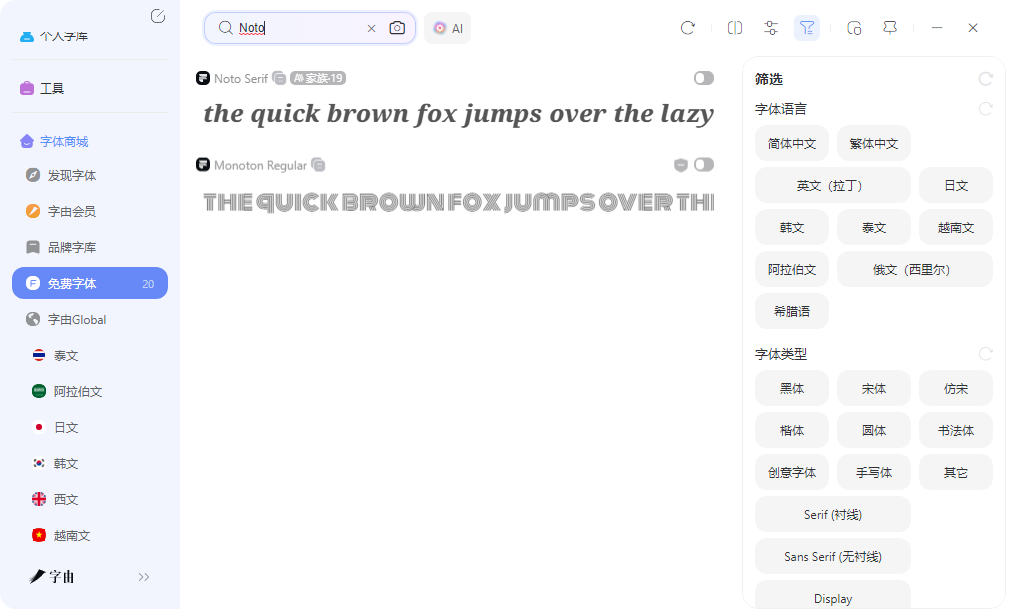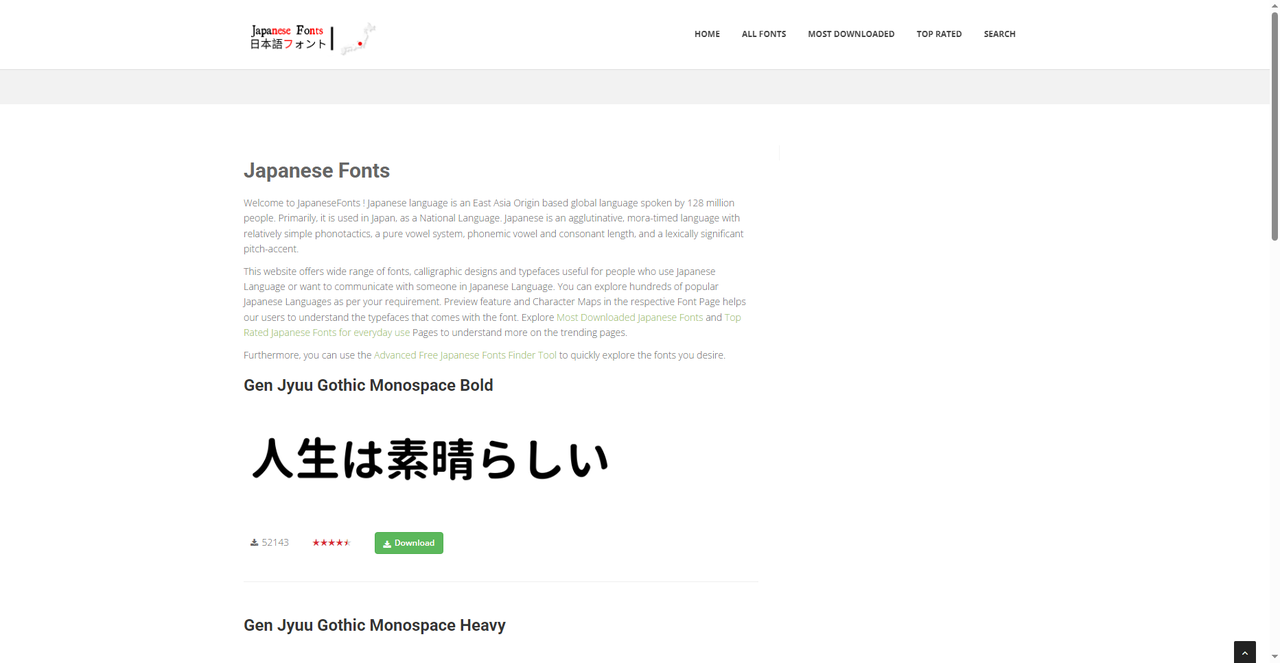
免费日文字体资源推荐,日式设计排版不用愁
做日系风格的海报、品牌包装或社交媒体配图,字体选对了,设计看起来才够味。市面上的日文字体大多需要付费,免费的那些又担心质量不行。其实有几个渠道可以获取到免费且品质不错的日文字体。今天推荐5个,从一键激活到在线转换,覆盖了不同需求。
字由是目前国内设计师使用频率较高的字体管理平台。它收录了超过10500款精选字体,其中免费商用字体超过3584款,而且每周都在更新资源库。字由对多语言的支持也比较到位。
筛选栏字体语言中直接勾选日文(Japanese),系统会自动列出所有已收录的日文字体。这些字体风格各异,有适合标题的粗体、适合正文的细体、适合品牌Logo的手写体等。用户还可以叠加筛选条件,比如同时勾选免费商用,系统会只显示可免费用于商业项目的日文字体。
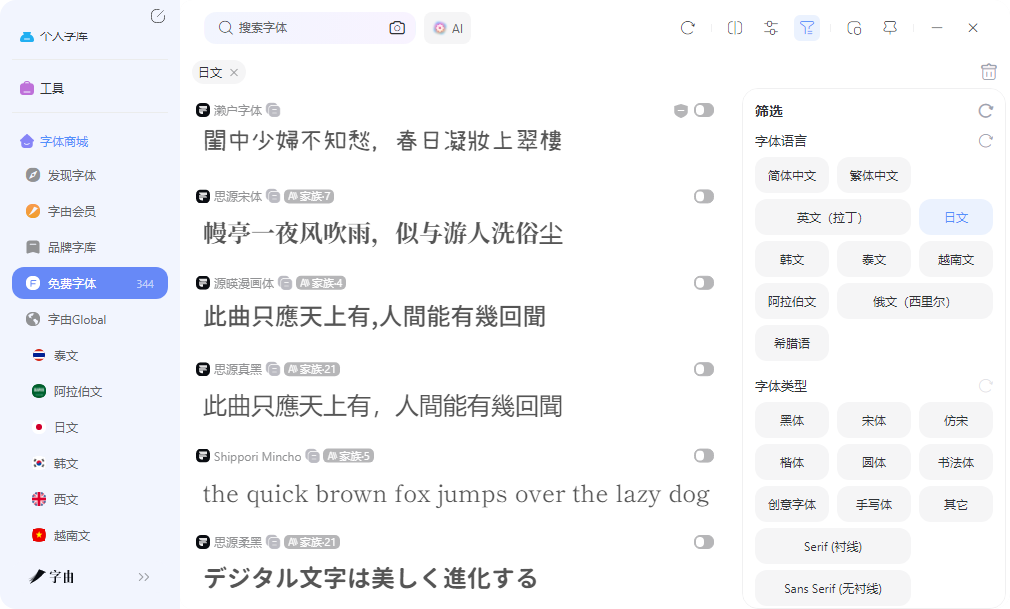
字由的筛选功能不只是分类展示,它的热度排序也值得一用。用户按热度从高到低排序,例如Noto等经典免费商用字体。思源黑体是Adobe与Google联合打造的开源字体,涵盖黑体、宋体等全套款式,支持简繁中文、日文、韩文及多种西文,7种字重能适配海报设计、品牌VI、文案排版等几乎所有场景。它基于SIL Open Font License 1.1协议,个人与商用全免费,无需标注出处,目前字由已完整收录。如果用户想做日系标题但不知道选哪款,直接跟着热度走基本不会出错。
2、JapaneseFonts
第二个网站是JapaneseFonts。它是一个专门收集日文字体的资源站,提供平假名、片假名、汉字、符号和英文数字的预览样式。网站收录了多款免费日文字体,下载量和使用热度都有标注。页面展示的Gen Jyuu Gothic Monospace Bold下载量超过5万次,Gen Jyuu Gothic Monospace Heavy下载量超过2.7万次,IPAMincho Regular下载量超过2.3万次,Noto Sans CJK JP Regular是Google Fonts出品的开源日文字体。每款字体都标注了下载量和星级评分,用户可以根据这些数据判断字体质量和受欢迎程度。JapaneseFonts不做字体托管,而是把提供日文字体的下载页面聚合在一起,配上标签分类和搜索功能。用户浏览字体预览后,可以点击链接到原网站下载。适合对日文字体有明确需求、愿意自己下载安装的用户。
3、Japanese Style
第三个网站是Japanese Style Fonts。它收录了105款受日式美学启发的风格字体,包括SAKURATA、Gang of Three等。这些字体虽然本身不是日文字符,但设计上借鉴了平假名、片假名的造型特征,适合日式主题的海报、餐厅菜单、商店Logo或横幅设计。该网站收录的字体中有不少明确标注免费商用。Kurohe字体由ArtiXLabs设计,带有圆润和锐利结合的日式风格,适用于活动海报、社交媒体、包装、Logo、品牌标识、T恤、杂志标题等多种场景,100%免费用于个人和商业用途。濑户字体是日本设计师濑户のぞみ创作的开源手写字体,线条柔和圆润,带有明显的手写痕迹,略向右倾斜模仿自然书写动态,采用SIL开源字体授权(OFL 1.1),允许个人和商业项目免费使用。用户可以从该网站获取TTF或OTF格式字体,也可以点击下载按钮后跳转获取Web字体。适合追求日式美学但不需要真实日文字符的用户。
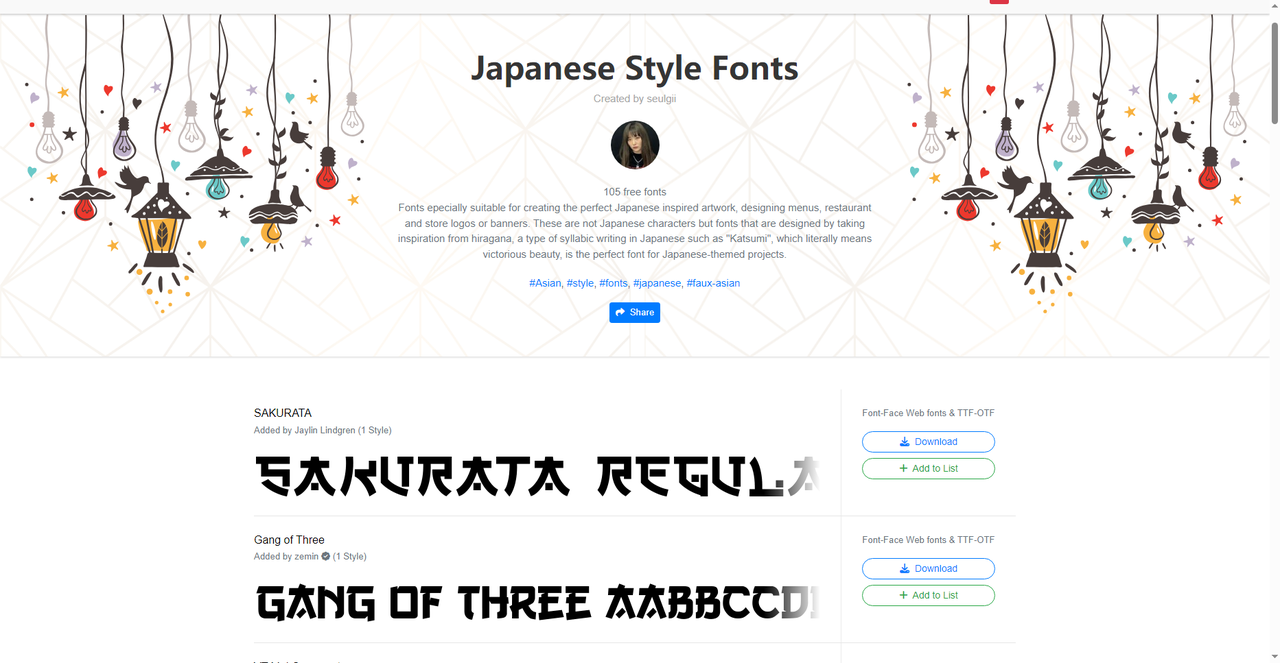
4、Japanese Font Style Generator
第四个工具是Japanese Font Style Generator。它是在线日文风格字符转换器,用户输入普通文字后,可转换为日式风格的假名类字符输出。工具内置了Della Gothic One、Kosugi、Kosugi Maru、M PLUS 1p等多种流行日文字体,用户可以直接预览不同字体的显示效果。该工具的核心优势是不需要安装任何字体文件,直接在浏览器中完成文字风格的转换和预览。用户调整字体大小、文字颜色、背景颜色后,页面实时刷新预览。转换后的结果可以通过截图保存或复制输出,适合临时需要一段日式风格文字但不想下载字体的用户。不需要注册,完全免费。
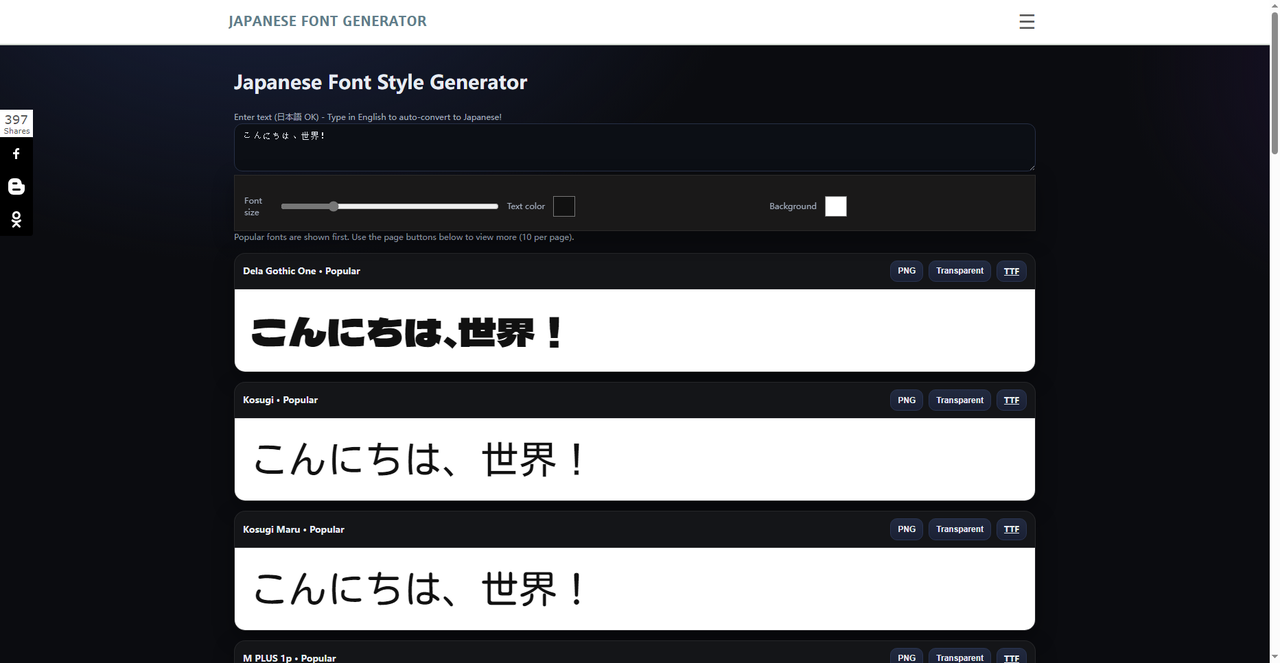
5、1001
第五个网站是1001的日文字体分类,收录了276款日文字体,涵盖brush、bold、katakana、handwriting、retro、ninja、sushi、modern、food、magazine、vintage等分类。用户可以在搜索栏中输入文字实时预览字体效果。该网站的核心功能是Commercial free筛选项。用户勾选Commercial free后,系统会筛选出可用于商业项目的免费日文字体。Mochi Boom DEMO、Amanojaku、JAPAN RAMEN、Sukajan Brush Demo等字体都在此列。每款字体标注了下载按钮和字体风格标签,用户确认授权类型后点击下载即可获取字体文件。适合需要字体文件本地安装、且对商用授权有明确要求的用户。